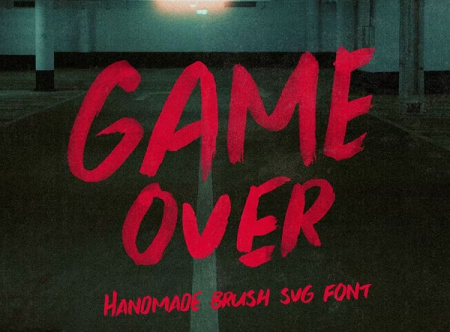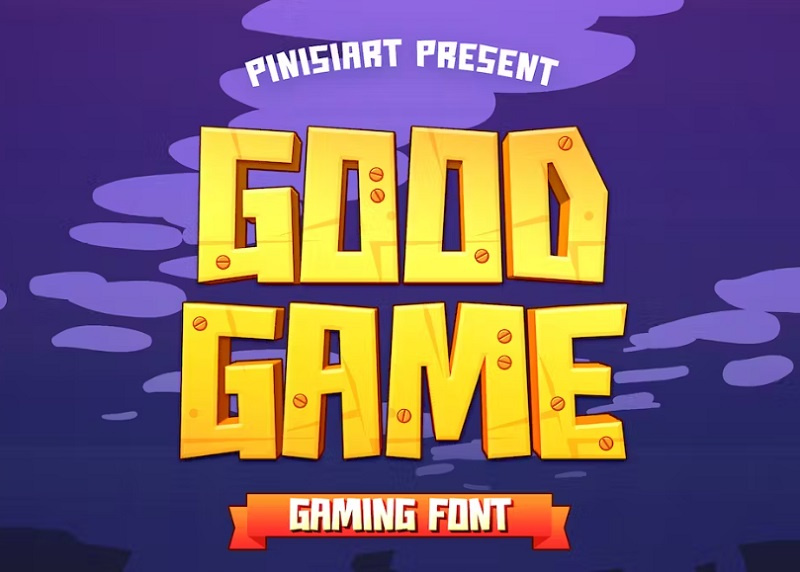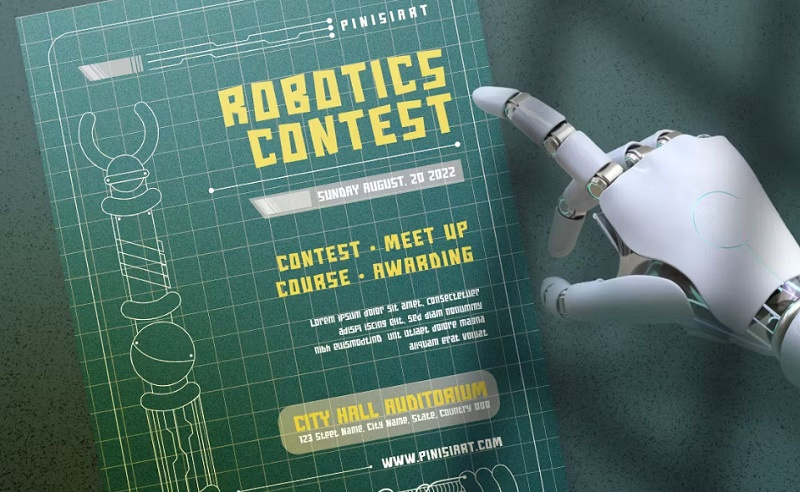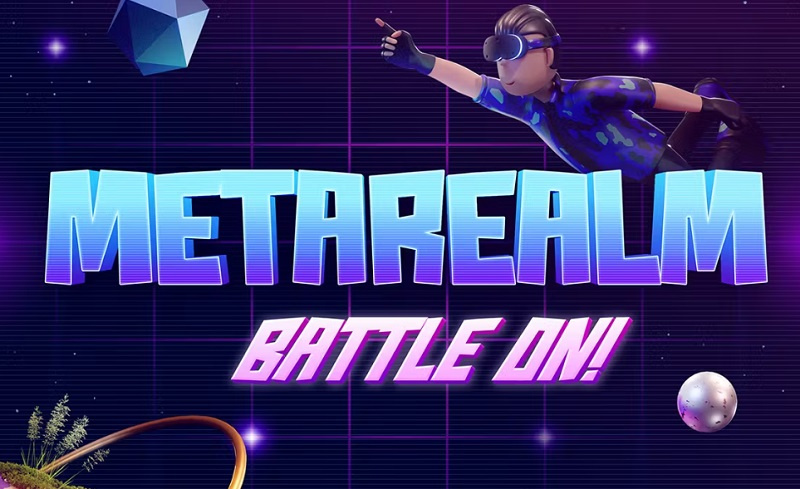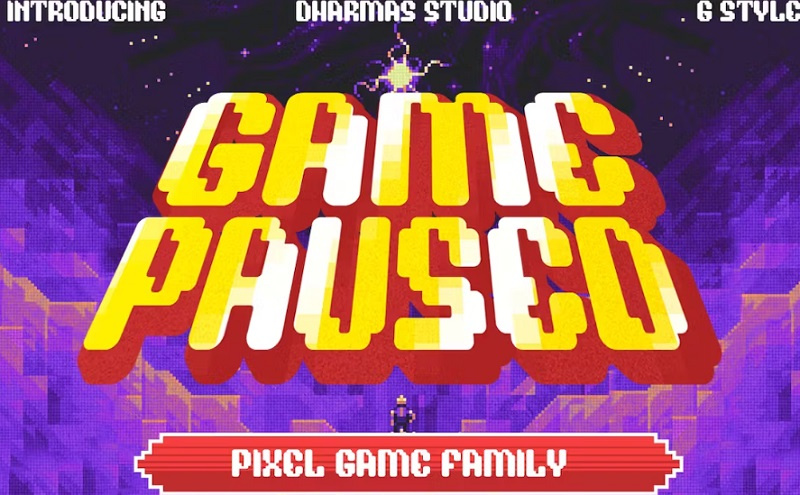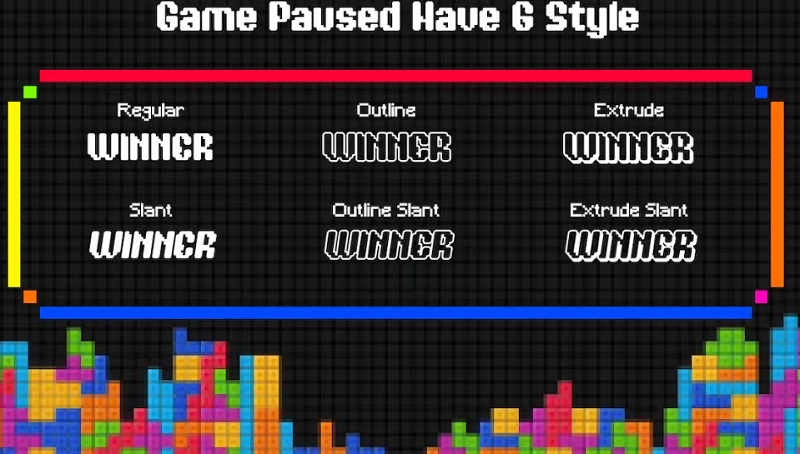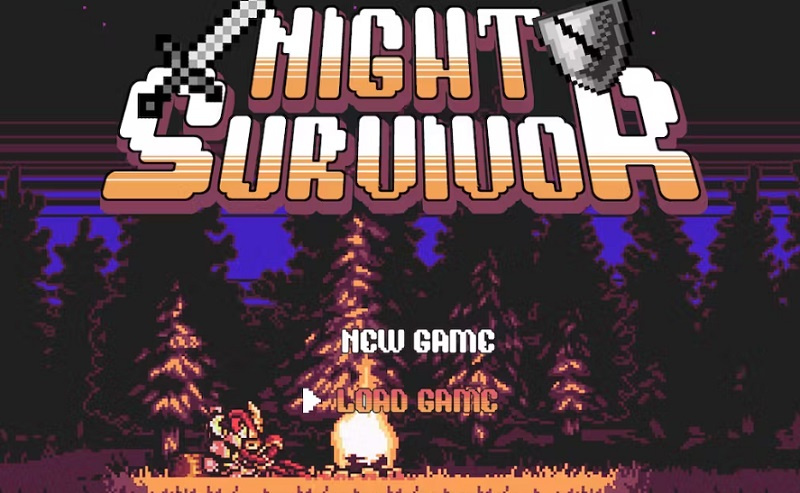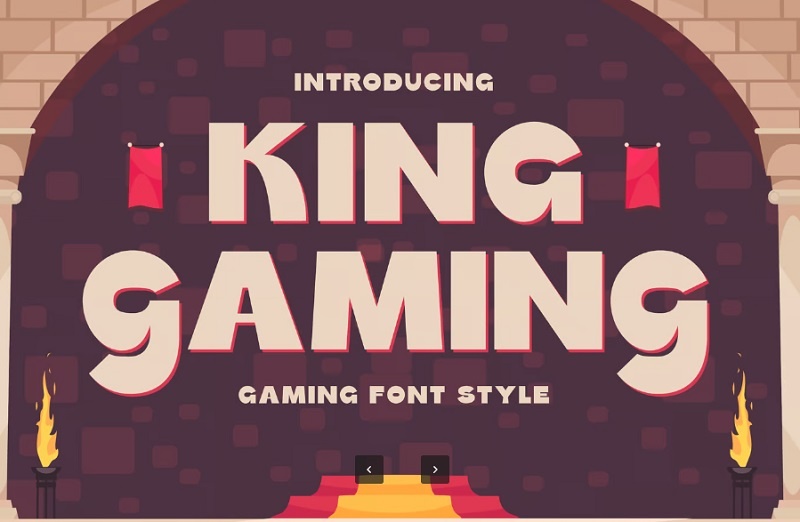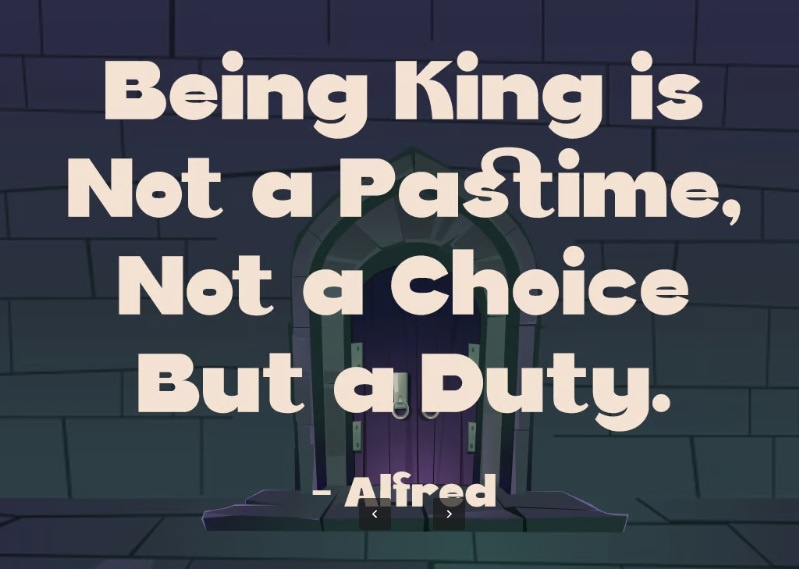
7 فونت انگلیسی گیمینگ High Gear Gaming Font
فونت انگلیسی گیمینگ
فونت انگلیسی گیمینگ شامل 7 فونت انگلیسی زیبا مخصوص بازی و گیم است که از سایت gfx در اختیار شما کاربران عزیز قرار داده شده است. این فونت انگلیسی گیم و بازی مناسب برای بازی‌های آنلاین با سرعت، پوسترهای رویدادهای نوجوانان، فونت وسایل مدرسه، پوسترها، عنوان فیلم‌ها، جلدهای یوتیوب، تصاویر کوچک یوتیوب، جلد صفحات رسانه‌های اجتماعی و غیره... می باشد.
این مجموعه فونت انگلیسی بازی و گیمینگ را برای بازی، گیم ، جلد کتاب، کتاب کودکان، کمیک، پوستر، بسته بندی، کالا، لوگوتایپ و موارد دیگر می توانید استفاده نمایید. برای دانلود این مجموعه از جی اف ایکس دانلود و مشاهده تصاویر این فونت های زیبا در ادامه با ما همراه باشید.
2- فونت انگلیسی برای گیم Game Paused
با این فونت زیبا به دنیای نوستالژی بازی و گیم های قدیمی خواهید رفت. این فونت انگلیسی برای گیم ترکیبی از حالات پیکسلی است که مناسب برای گیمیر ها، انواع بازی، گیمینگ، بازی های پیکسلی می باشد. این فونت انگلیسی برای بازی شامل فایل هایی با فرمت TTF, OTF, WOFF, and WOFF2 است.
3- دانلود فونت گیم و بازی انگلیسی
King Gaming یک فونت بازی و گیم است که یک انتخاب ایده آل برای هر فیلم، بازی و گیمینگ است. این فونت انگلیسی گیمینگ شامل فایل های OTF، TTF، WOFF، WOFF2 می باشد.
4- دانلود فونت انگلیسی گیمری برای بازی‌های کامپیوتری
اگر به‌ دنبال دانلود فونت انگلیسی گیمری هستید که با فضای هیجان‌ انگیز بازی‌ های کامپیوتری هماهنگ باشد، این مطلب مناسب شماست. استفاده از فونت‌ های انگلیسی گیمینگ در طراحی لوگو، پوستر یا رابط کاربری بازی می‌ تواند تأثیر چشم‌ گیری در تجربه‌ی بصری کاربر ایجاد کند. این فونت‌ ها معمولاً با الهام از سبک‌ های علمی‌تخیلی، اکشن، رترو یا مدرن طراحی می‌شوند و حس دنیای گیم را به‌خوبی منتقل می‌ کنند.  استفاده از یک فونت انگلیسی گیمری مناسب می‌ تواند تجربه‌ بصری کاربر را چند برابر جذاب‌ تر کند و برند بازی شما را حرفه‌ ای‌ تر نشان دهد.
✅ نام فونت انگلیسی1: High Gear - Gaming Font
✅ نام فونت انگلیسی2: Game Over Brush
✅ نام فونت انگلیسی3: Gamer Station
✅ نام فونت انگلیسی4: Good Game
✅ نام فونت انگلیسی5: Game Paused
✅ نام فونت انگلیسی6: King Gaming
✅ نام فونت انگلیسی7: Mbrasak - Sports Gamer